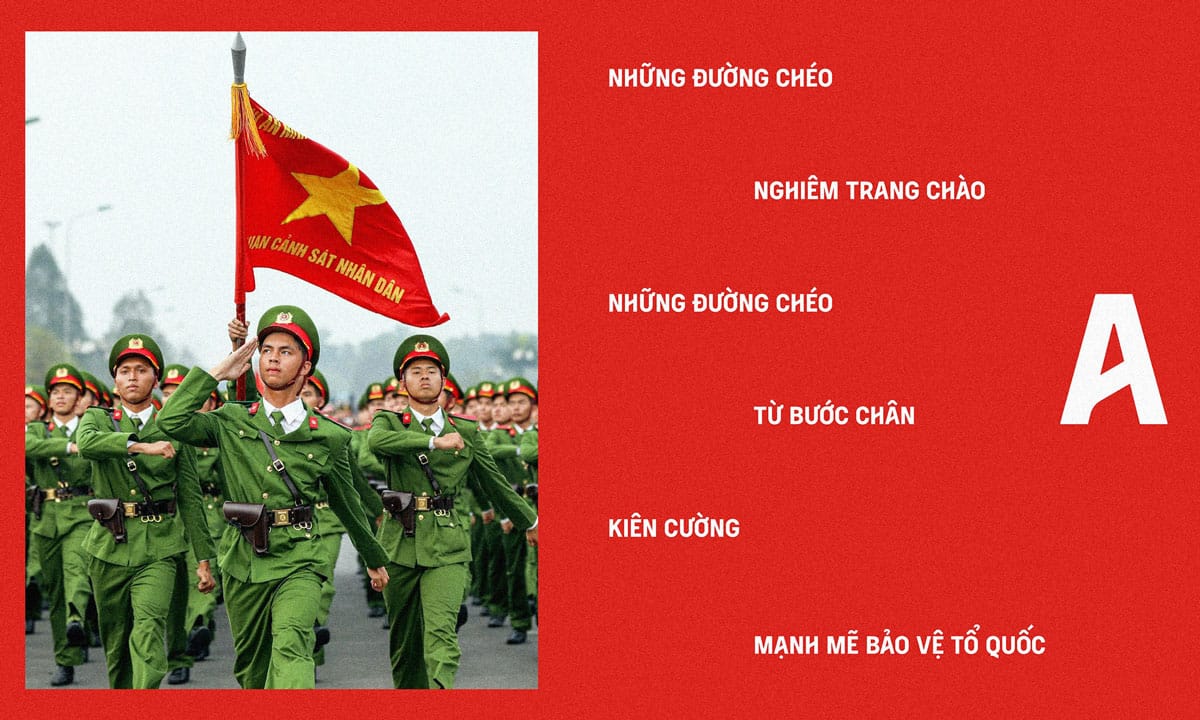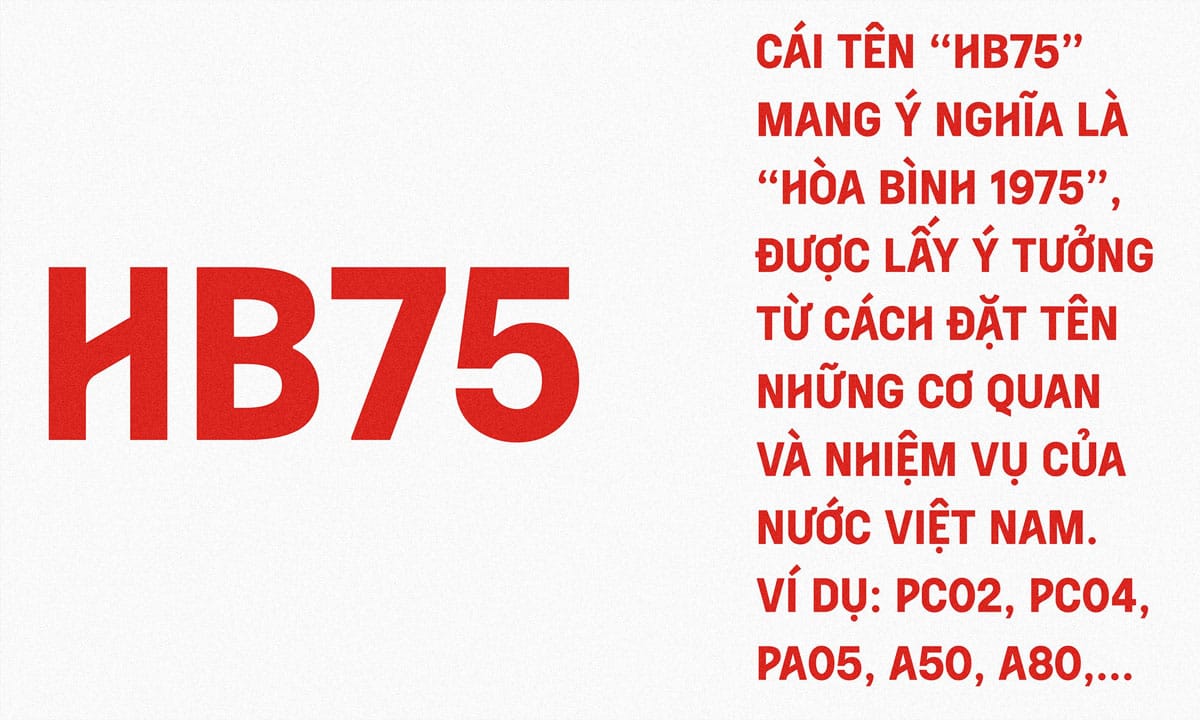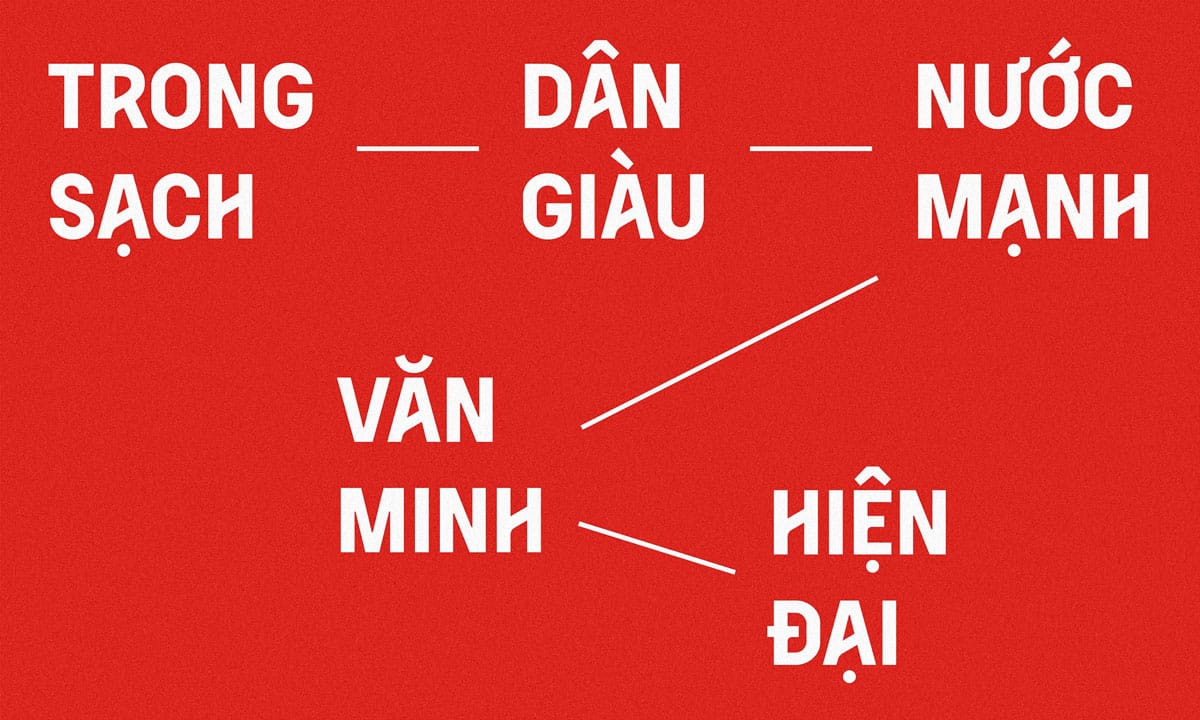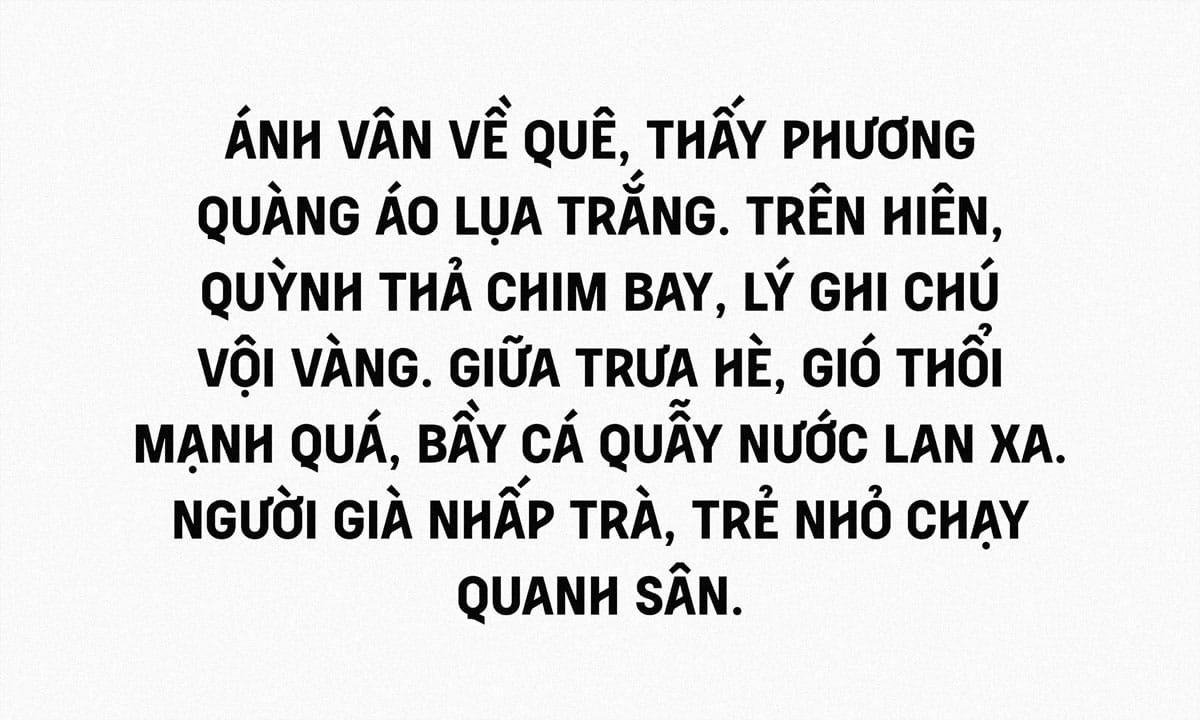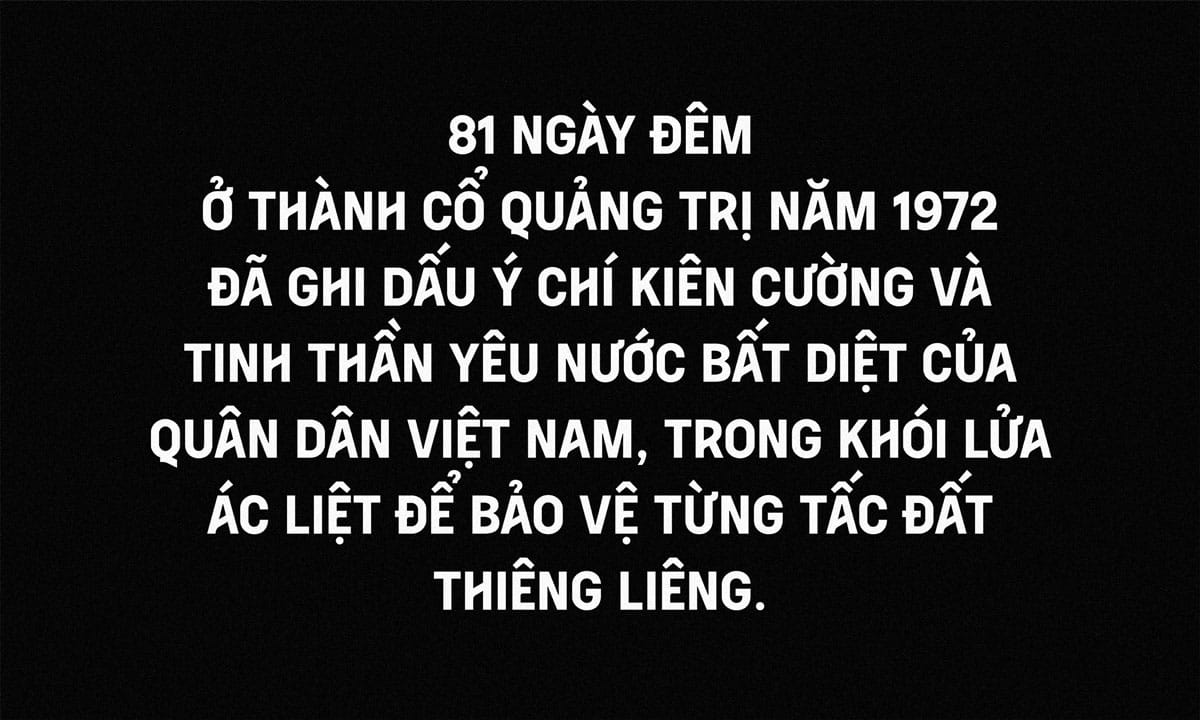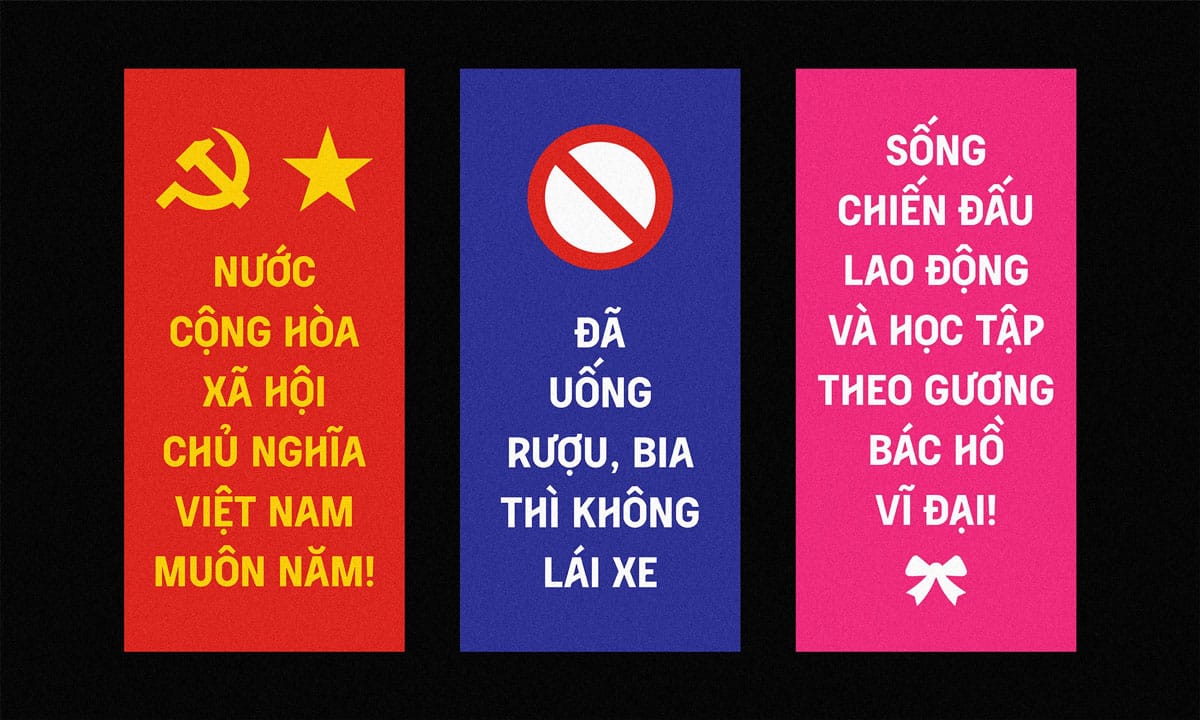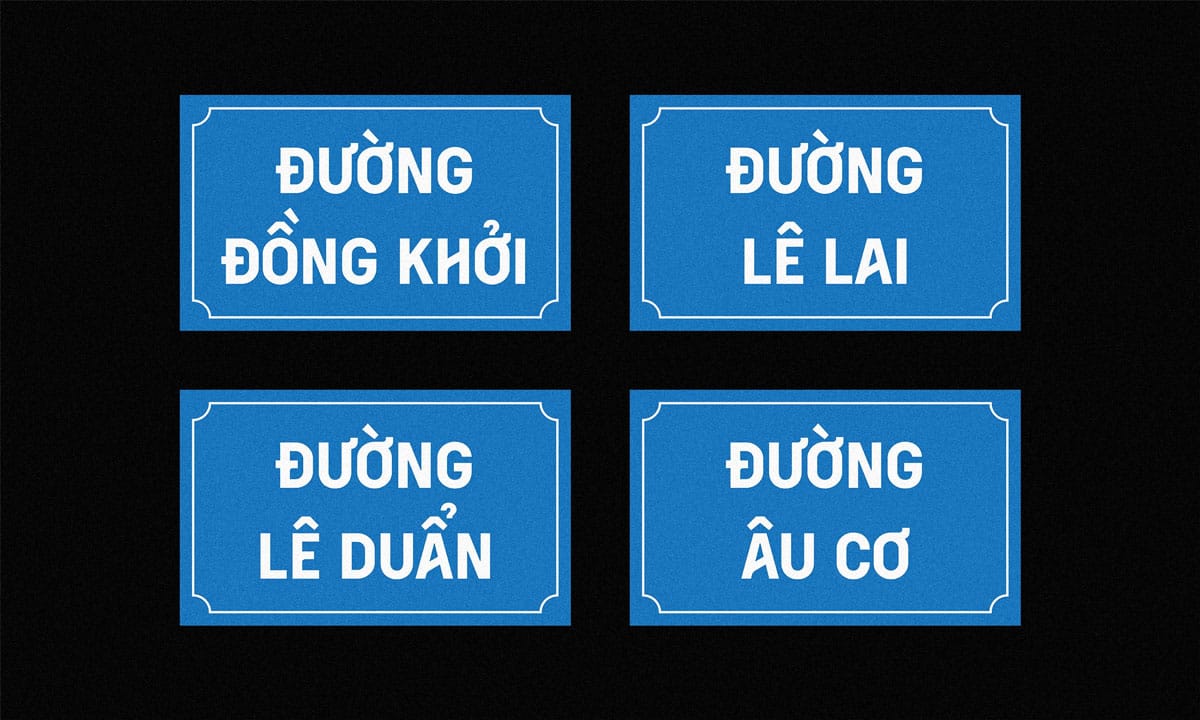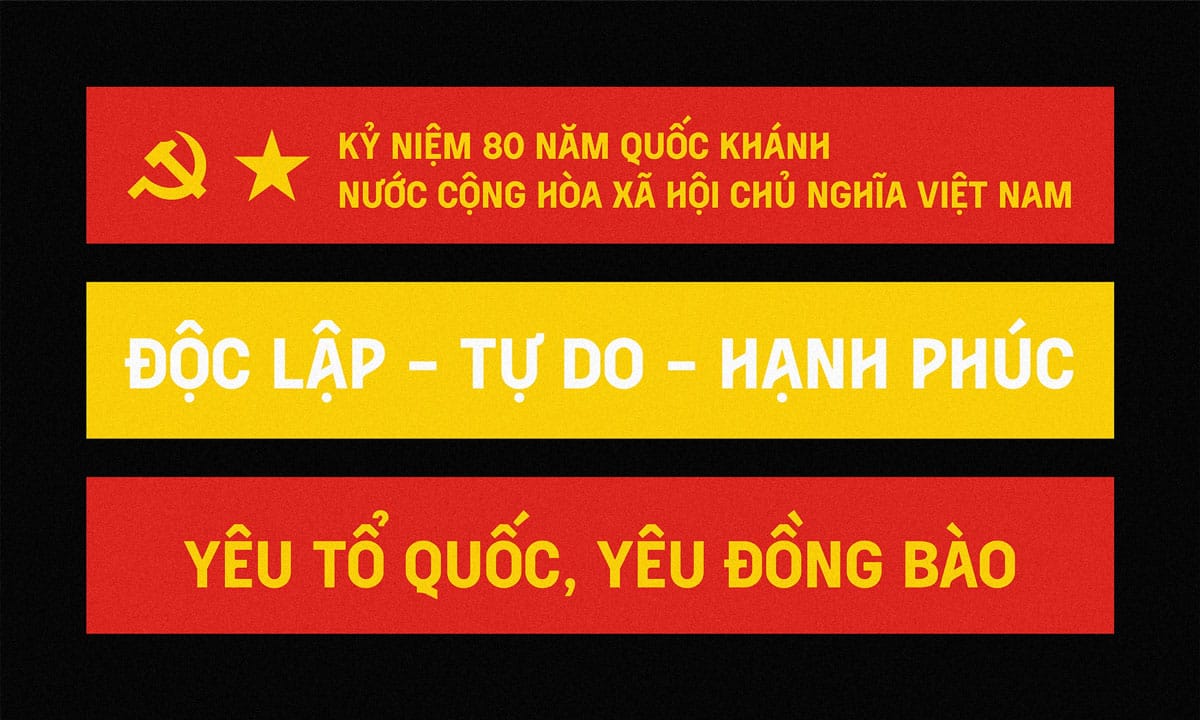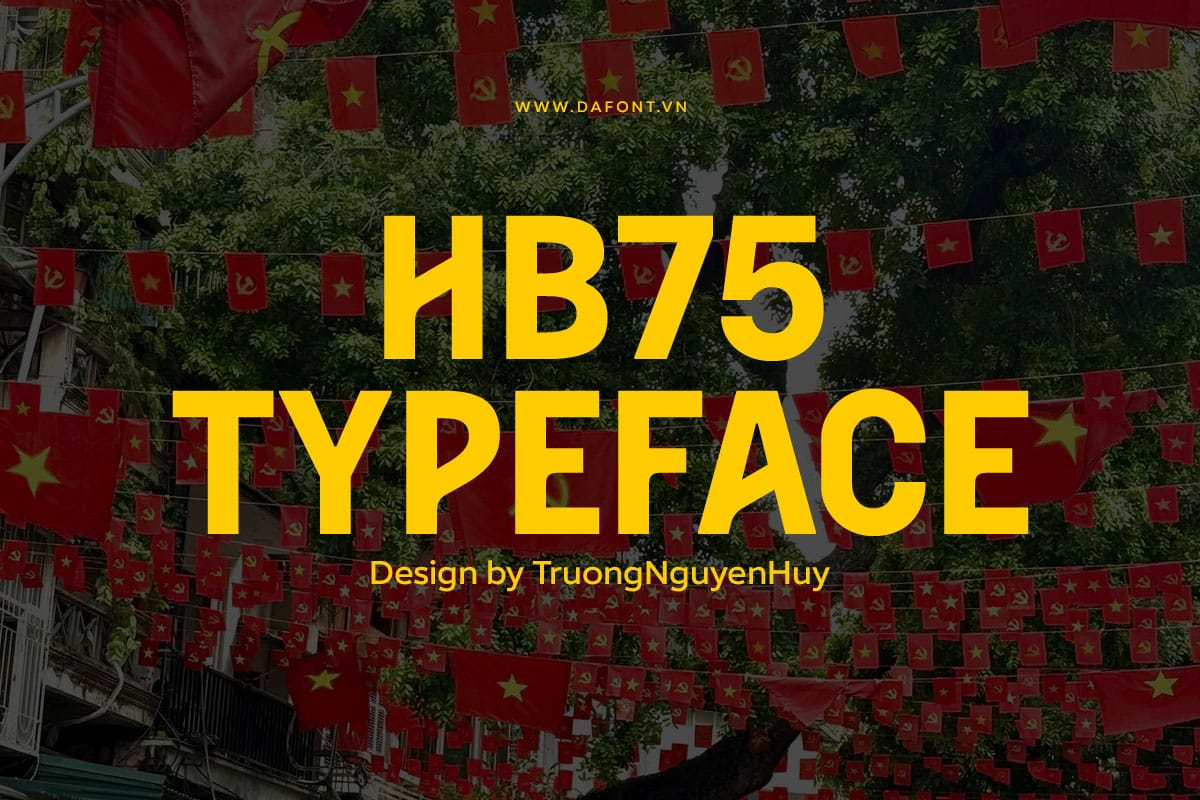
HB75 – Phông chữ mang tinh thần người lính Việt Nam
HB75 là một phông chữ độc đáo được lấy cảm hứng từ hình ảnh người lính và người công an nhân dân Việt Nam – những con người kiên định, kỷ luật và tận tụy vì Tổ quốc. Phông chữ được thiết kế bởi Trương Nguyên Huy, nhằm tôn vinh tinh thần mạnh mẽ, nghiêm trang nhưng vẫn gần gũi, quen thuộc với người Việt.
Nguồn cảm hứng và thiết kế
HB75 được xây dựng trên nền tảng phông chữ không chân (sans-serif) – kiểu chữ vốn thường xuất hiện trong các ấn phẩm, biển báo và tiêu đề chính trị – xã hội. Từ đó, phông chữ mang hơi thở quen thuộc của đời sống Việt Nam: từ biển tên đường, bảng chỉ dẫn, đến băng rôn tuyên truyền – những hình ảnh quen thuộc gắn liền với ký ức tập thể của nhiều thế hệ.
Điểm đặc trưng trong thiết kế của HB75 là những đường chéo mạnh mẽ được đưa vào cấu trúc con chữ. Hình ảnh này được gợi lên từ động tác chào và bước điều lệnh của người chiến sĩ, tượng trưng cho ý chí kiên cường, tinh thần kỷ luật và lòng yêu nước mãnh liệt. Sự kết hợp giữa tính hiện đại và tinh thần truyền thống giúp HB75 vừa phù hợp cho các thiết kế mang tính nghi lễ, vừa có thể ứng dụng linh hoạt trong các dự án sáng tạo đương đại.
Ý nghĩa tên gọi “HB75”
Tên gọi HB75 được viết tắt từ cụm từ “Hòa Bình 1975” – mốc son lịch sử đánh dấu ngày đất nước hoàn toàn thống nhất. Cách đặt tên này lấy cảm hứng từ quy ước mã hiệu của các cơ quan, đơn vị trong hệ thống Nhà nước Việt Nam, như: PC02, PC04, PA05, A50, A80…
Chính sự ngắn gọn và rõ ràng này khiến font trở nên mạnh mẽ, súc tích và mang đậm dấu ấn “hành chính Việt Nam” – vừa trang nghiêm, vừa quen thuộc.